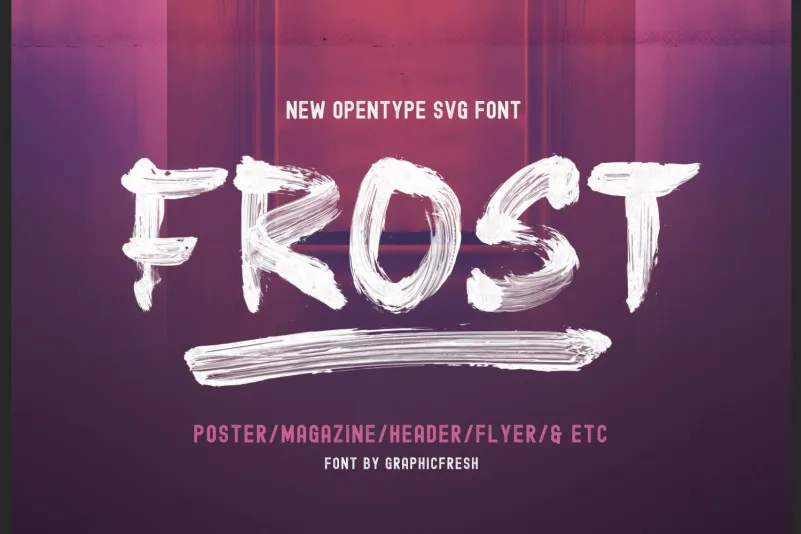
Frost Vector Font – Download Grátis
Esta é uma bela fonte de exibição criada pela Graphicfresh com estilo de traço feito à mão rústico. Esta fonte foi projetada usando um pincel digital que tem um traço áspero, resultando em caracteres fortes e belos. Ela se aplica perfeitamente para aumentar a atratividade do produto ao aplicá-la, tornando-o mais único. Esta font é ótima para criar preview e capas, projetos de logotipos, design da rua, criações de camisas e outras necessidades gráficas. Se procura uma alternativa àcentuada e moderna, esta font pode ser a sua escolha perfeita, proporcionando um visual chamativo e distinto. Seja para criar um logotipo impactante ou decorar uma peça de design gráfico com estilo, esta font é certamente uma boa opção. Ela oferece flexibilidade para diferentes usos gráficos, desde projetos digitais até materiais impressos, garantindo um resultado personalizado e único.